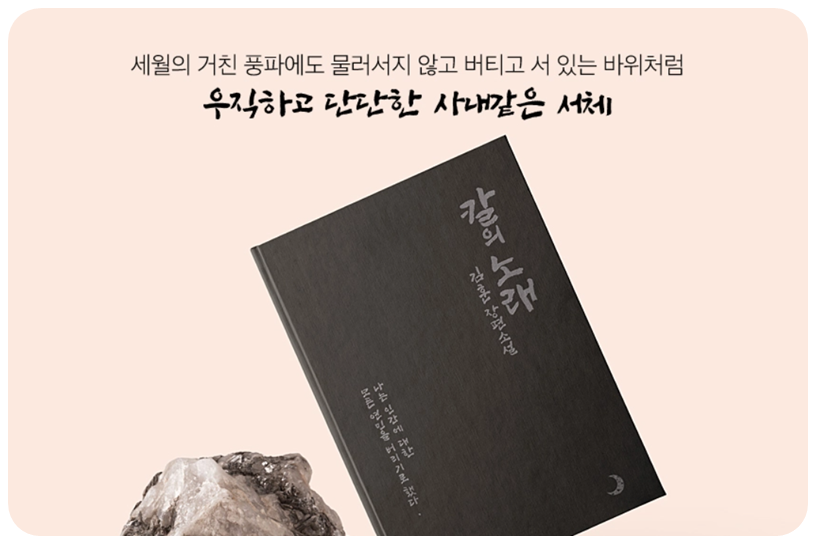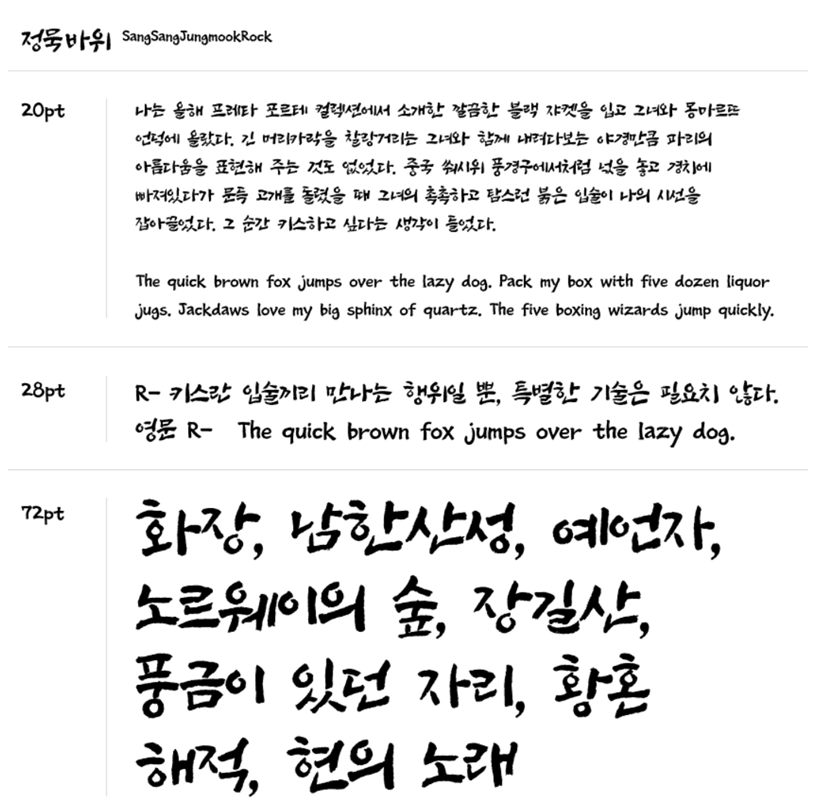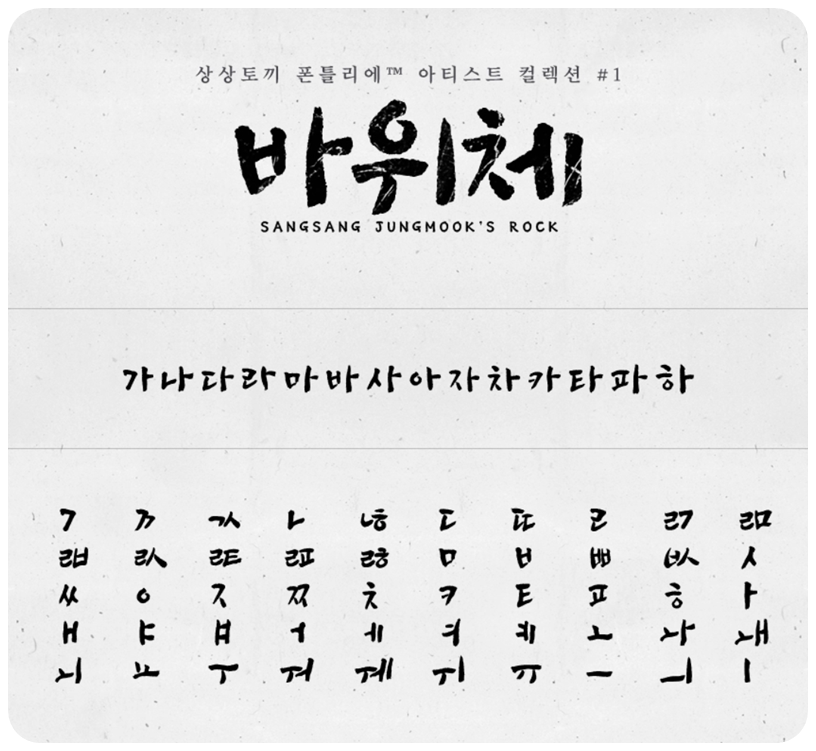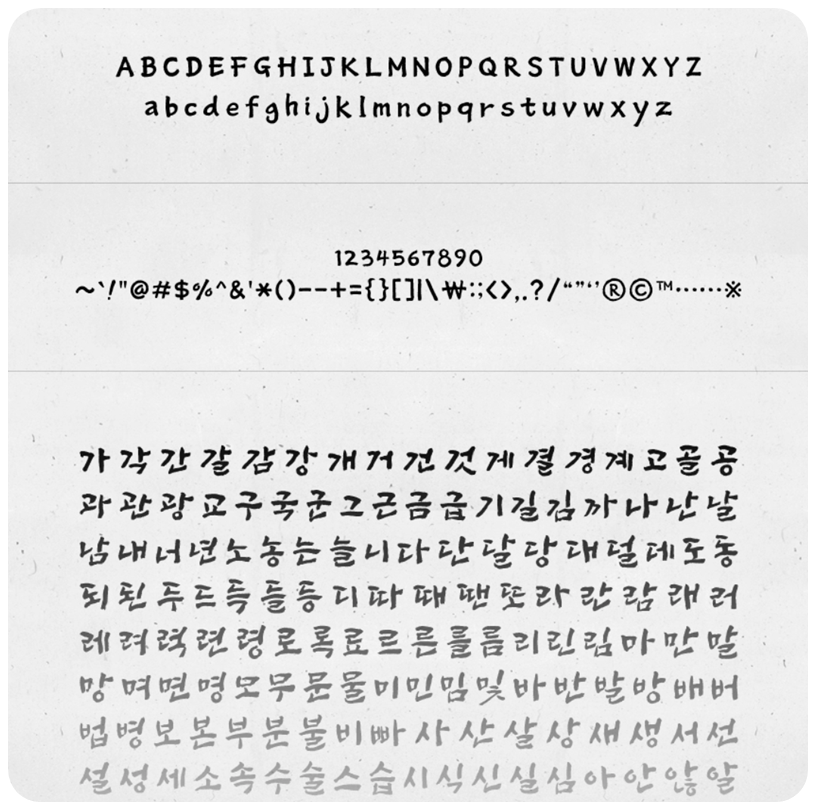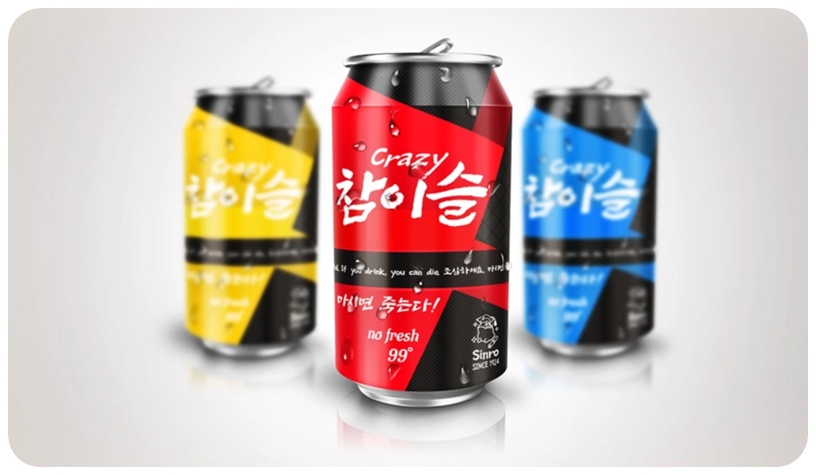
강렬하고 묵직한 느낌의 캘리그라피 폰트를 찾고 있다면 이 서체를 놓치지 마세요.
대한민국 대표 캘리그래퍼의 필체를 담은 ‘정묵 바위’ 폰트는 한 글자만으로도 분위기를 압도합니다.
정묵 바위 폰트란?
‘정묵 바위’는 대한민국 대표 캘리그래피 작가 정묵 김덕수 선생님의 손글씨를 기반으로 제작된 서체입니다.
단단하고 우직한 느낌을 강조한 디자인으로, 강한 메시지를 전달할 때 특히 효과적인 폰트입니다.
폰트 특징
✔️ 유명 캘리그래퍼 손글씨 기반 제작
✔️ 묵직하고 강렬한 붓글씨 스타일
✔️ 포스터, 타이틀, 브랜딩에 최적화
✔️ 시선을 사로잡는 임팩트 있는 디자인
특히 제목용으로 사용했을 때 존재감이 확실하며, 한 글자만으로도 강한 인상을 남길 수 있습니다.
폰트 구성 정보
| 항목 | 내용 |
|---|---|
| 서체명 | 정묵 바위 Regular |
| 한글 | 약 2,479자 |
| 영문 | 52자 |
| 기호 | 약 54자 |
활용 추천
📌 영화/유튜브 썸네일 타이틀
📌 포스터 및 광고 디자인
📌 브랜드 슬로건 강조
📌 강렬한 메시지 전달 콘텐츠
특히 강한 메시지를 전달해야 하는 디자인에서 최고의 효과를 발휘합니다.
Q4. 어떤 디자인에 적합한가요?
포스터, 타이틀, 썸네일, 광고 등 강렬한 인상을 주는 디자인에 적합합니다.
정묵 바위 폰트는 강한 존재감과 감성을 동시에 담은 캘리그래피 서체입니다.